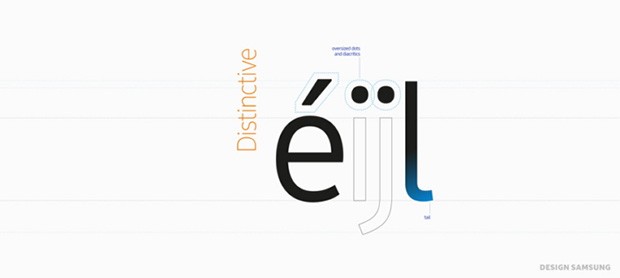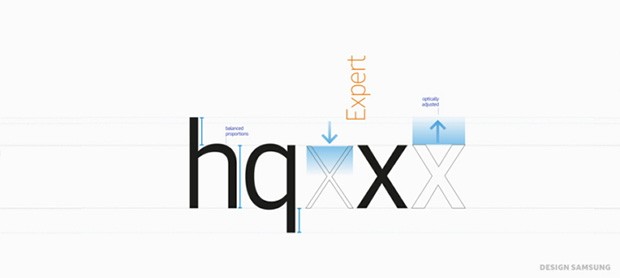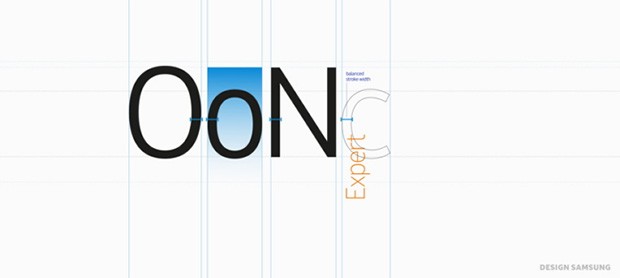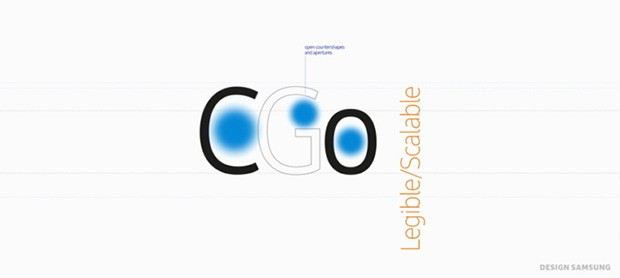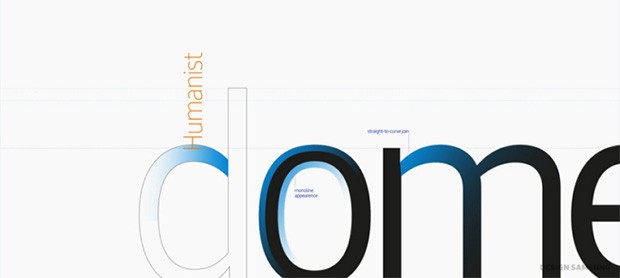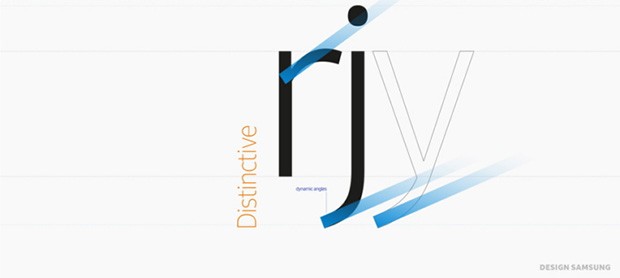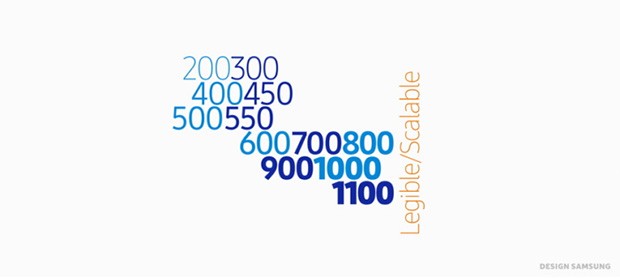
Il raggio d’azione di Samsung si estende in tutto il mondo, coprendo ambiti che vanno da quello relativo ai dispositivi mobile fino ai sistemi per l’intrattenimento domestico, dagli elettrodomestici ai computer portatili. Oggi il gruppo sudcoreano annuncia la nascita di SamsungOne, un carattere tipografico pensato e concepito per veicolare un’unica identità, indipendentemente dalla tipologia di prodotto o servizio offerto.
SamsungOne
Un font, dunque, realizzato da un team di designer che ha tenuto in considerazione richieste ed esigenze ben specifiche. Innanzitutto la necessità di adattarsi al meglio ai 26 sistemi di scrittura utilizzati negli oltre 400 linguaggi del pianeta, per un totale di 25.000 e più simboli, lettere, numeri e glifi. L’intento è dunque quello di offrire un’esperienza universale, utilizzando un carattere che sia identificativo per il brand, immediatamente riconoscibile. Non importa in che modo gli utenti interagiranno con il marchio: rispondendo ad una telefonata, guardando un film in salotto, aprendo il portello di un frigorifero o ascoltando musica dagli speaker.
SamsungOne renderà ogni dispositivo parte di un ecosistema più ampio, strutturato e integrato. Di seguito l’intervento filmato di Neville Brody, tipografo di fama mondiale, che ha lavorato in prima persona al progetto.
Principi tipografici
L’azienda spiega la nascita di SamsungOne come un percorso attraverso il quale dar vita ad un carattere in grado di essere anzitutto accessibile, ben leggibile indipendentemente dalla dimensione delle lettere e dal supporto utilizzato. Al tempo stesso, il font è stato creato per avere un look moderno e sofisticato, in linea con l’approccio innovativo utilizzato nella realizzazione dei prodotti. Niente orpelli decorativi, ma un lettering essenziale, elegante, che va dritto al punto. Cinque i principi tipografici assunti come linee guida.
- Umanista: SamsungOne mischia un tratto semplice, di larghezza costante, con dettagli calligrafici.
- Distintivo: angoli dinamici nascono all’unione di un arco con una curva per creare un design consistente.
- Universale: come parte di una famiglia globale, SamsungOne è localizzato nei vari paesi, pur rifacendosi ad un unico DNA.
- Esperto: un approccio manuale alla creazione del font e in particolare dei dettagli ha permesso di trovare il giusto equilibrio tra forme ascendenti e discendenti.
- Leggibile e scalabile: le lettere sono disegnate per essere visualizzate in maniera funzionale sia a piccole che grandi dimensioni.
In altre parole, Samsung mette in campo un’iniziativa già vista in passato per altre aziende del settore hi-tech come Google con Roboto, Apple con San Francisco e Microsoft con Segoe.